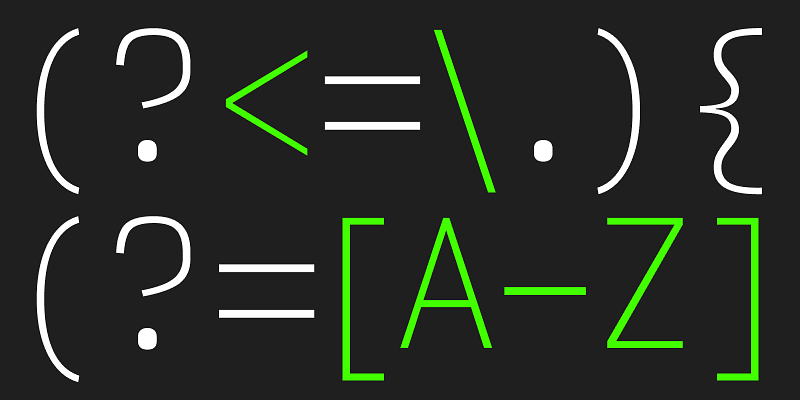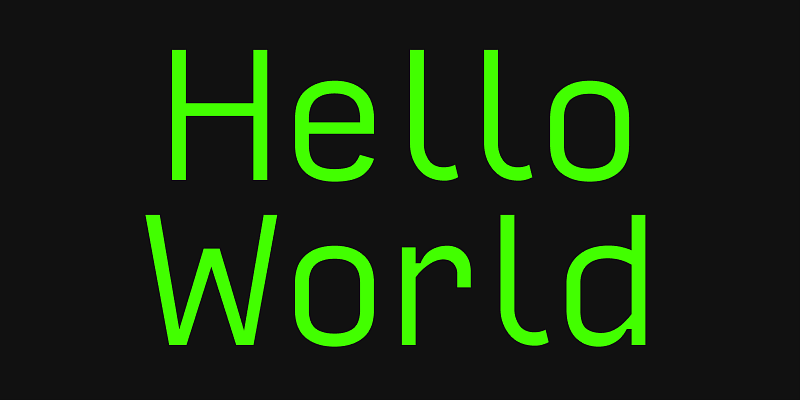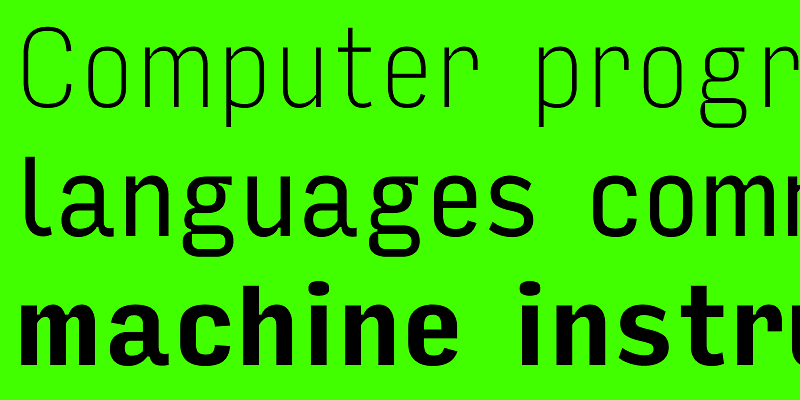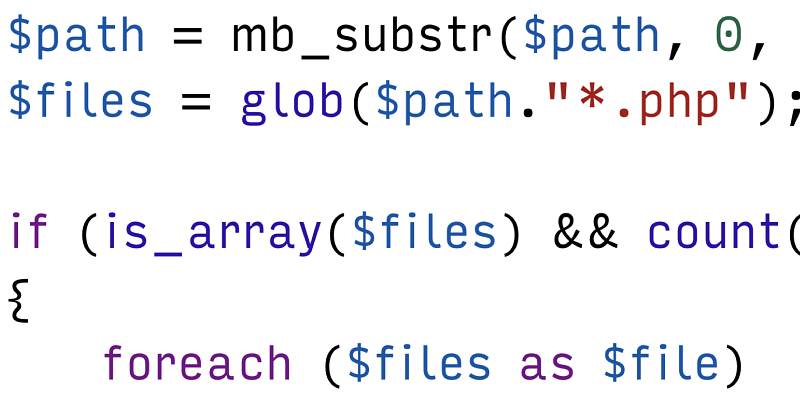
多くのプログラマーがそうであるように、David Jonathan Ross も自分のコードに等幅フォントを使用していました。しかしやがて、その慣習に疑問を持ち、データとプログラミングの美に対して新鮮なアプローチで答えるようになったのです。「Input」は初期のコンピューターコンソールからインスピレーションを得た書体ですが、コーディング環境が技術的な制限を克服し、ディスプレイを完全に制御できる、豊かなタイポグラフィに満ちた未来を展望しています。
David Jonathan Ross は、カスタム書体や小売り用書体デザインに使うあらゆる形と大きさの文字をマサチューセッツ西部の森にある自分のスタジオで作成しています。ロサンゼルス出身の彼は、Hampshire College で書体作りを始め、2007 年に The Font Bureau に入社してベジェ曲線の扱いの腕前を磨きました。現在は、自社である DJR で書体デザインを公開するかたわら、Type Network を使ったプロジェクトや、Font of the Month Club 向けの珍しい表示用書体の開発に取り組んでいます。